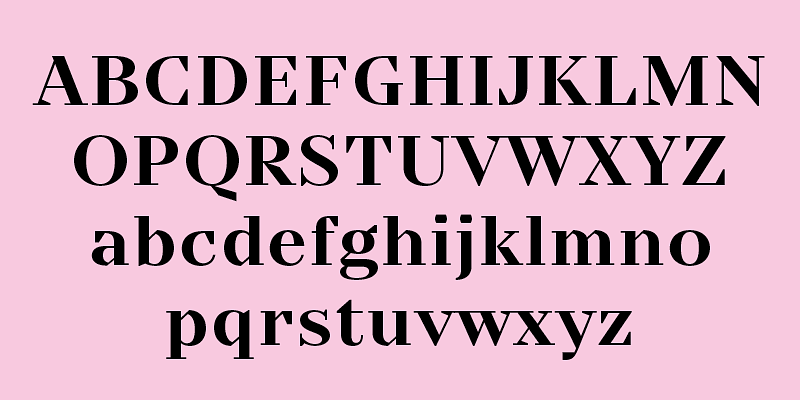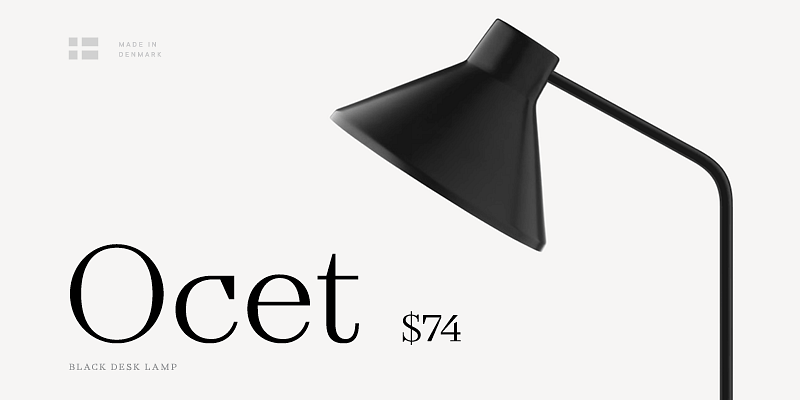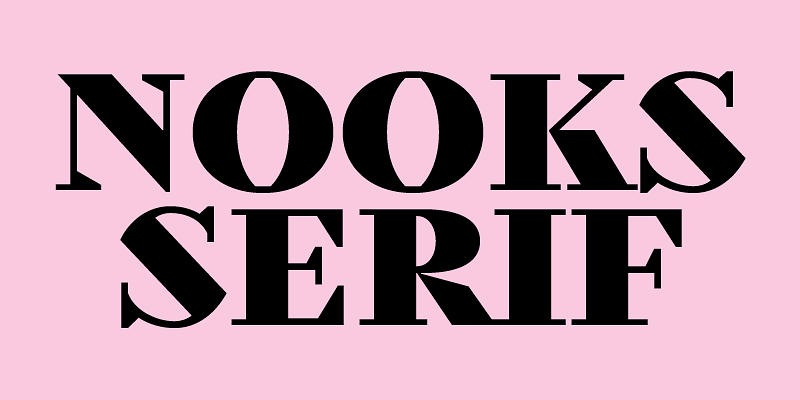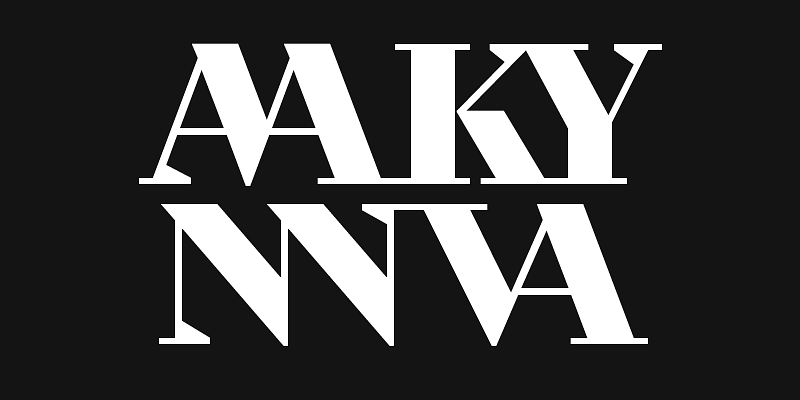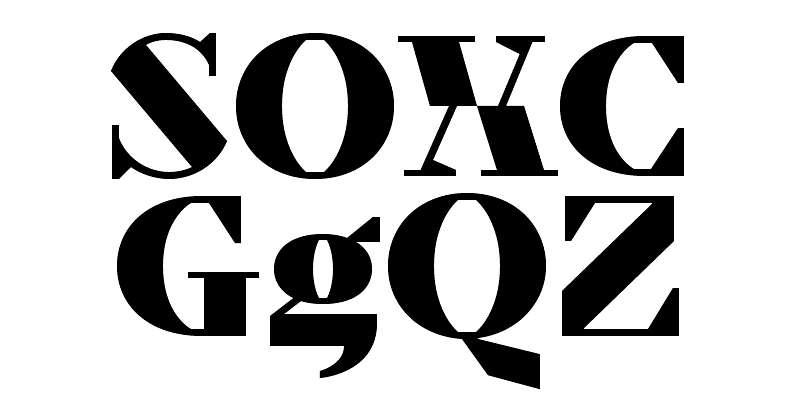
TT Nooks est une famille de polices expérimentale qui comprend un empattement à contraste élevé, TT Nooks, et un italique droit, TT Nooks Script. Malgré la différence de style, les deux sous-familles s’entendent bien, en partie grâce à leurs proportions similaires. La sous-famille principale est TT Nooks, une police à empattement élégante et très contrastée avec une légère touche d’égocentrisme. TT Nooks Script est une famille complémentaire conçue pour étendre harmonieusement la famille principale et étendre sa portée.